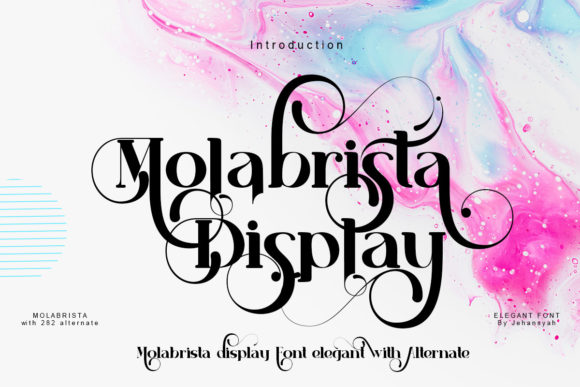
Creativefabrica Molabrista Font 2021
[Creativefabrica] Molabrista Font (2021)
Molabrista - это элегантный и выразительный шрифт с засечками.
Он добавит роскошную искру в любой дизайнерский проект, который вы хотите создать!